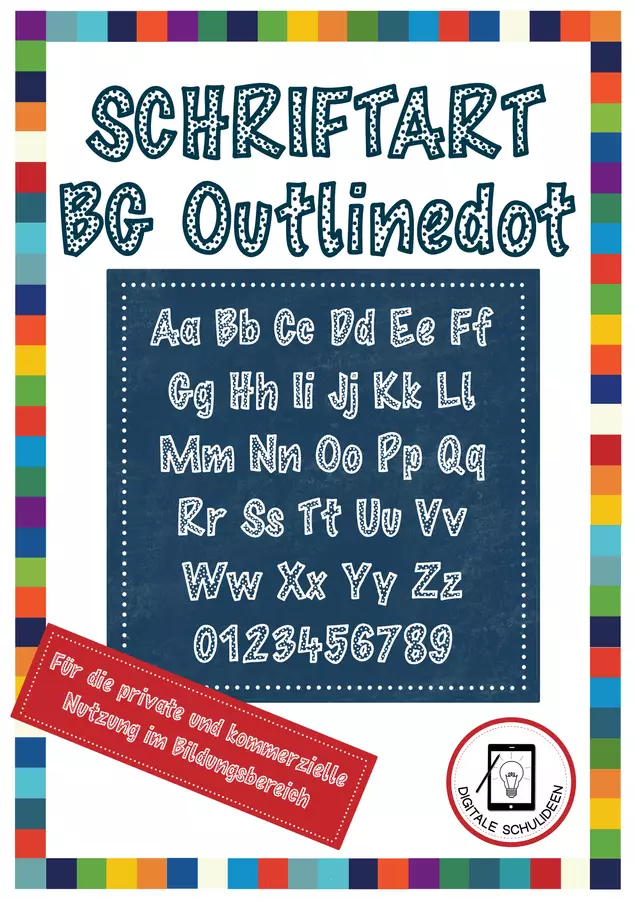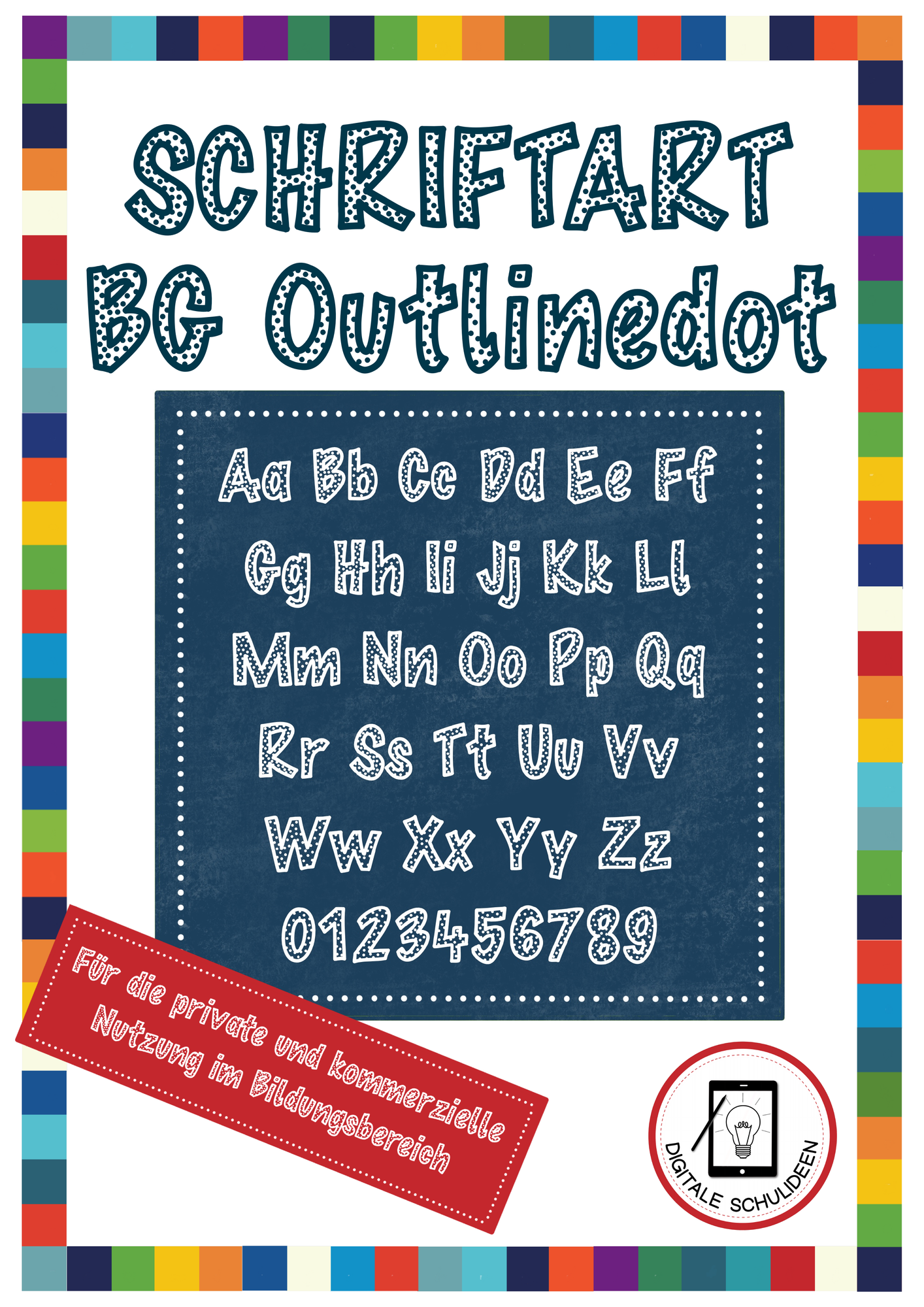
Praktische Schriftart mit Punkten und Outline für kommerzielle Nutzung
Die BGOutlinedot Schriftart bietet eine klare und kreative Option für verschiedene Designs. Besonders vorteilhaft ist die kommerzielle Nutzungsberechtigung, die es ermöglicht, die Schrift in eigenen Bildungs-Projekten zu verwenden. Mit ihrer Kombination aus Punkten und Outline eignet sie sich gut für auffällige, stilvolle Texte. Eine vielseitige und nützliche Schriftart für kreative Projekte!
Ich mag deine Schriften total und diese ist dir auch richtig gut gelungen. Auf eigenen Arbeitsblättern wirkt sie klasse! Sie ist zwar dekorativ, trotzdem aber gut lesbar 👍
Wiedermal eine tolle Schriftart, die ich für mein eigenes Material einsetzen kann. Meiner Meinung nach gut für Material für Klasse 1 für Nachspurübungen geeignet.